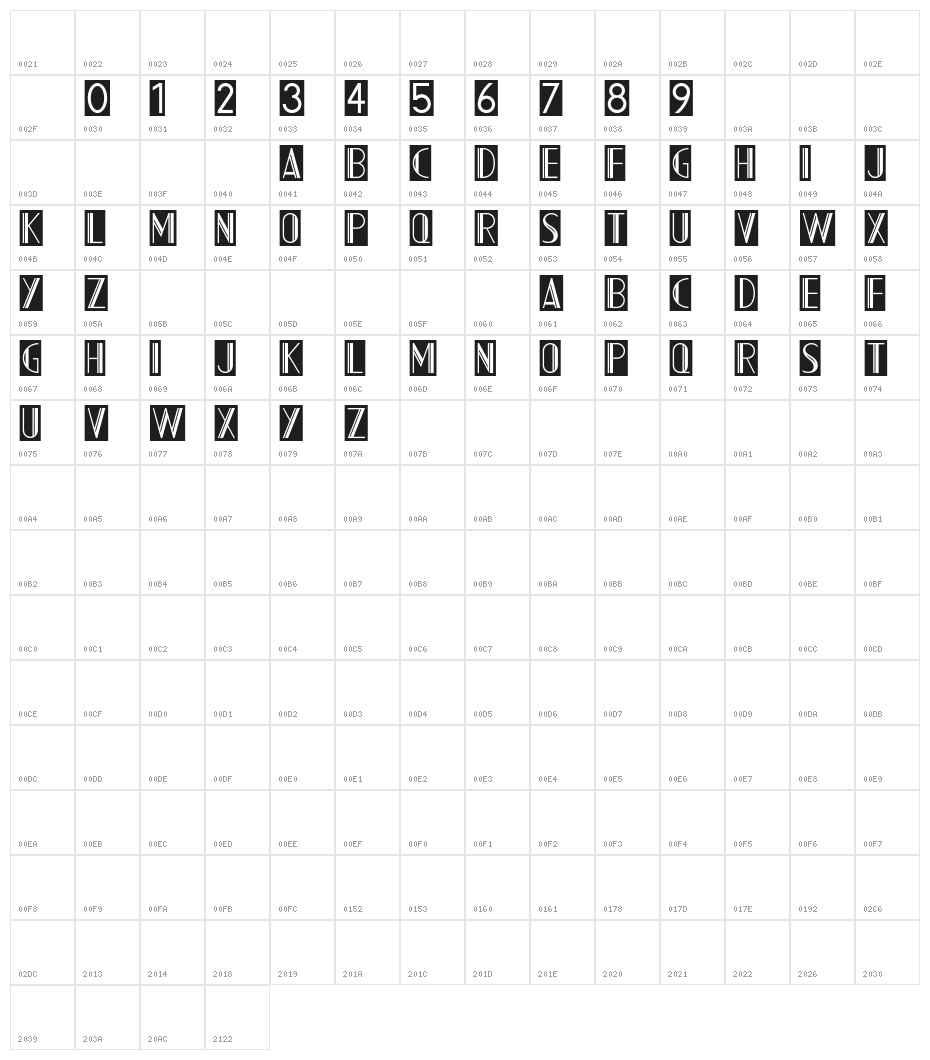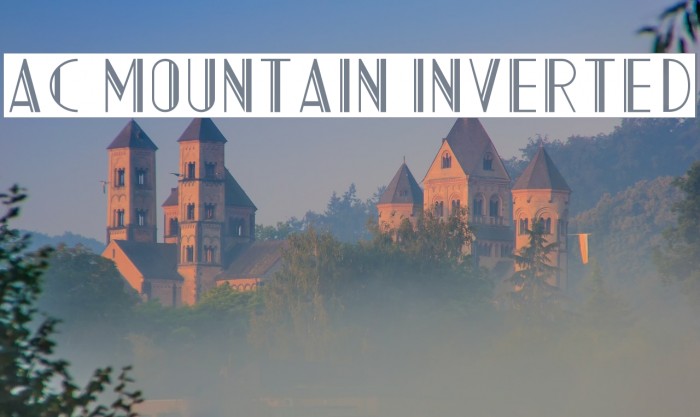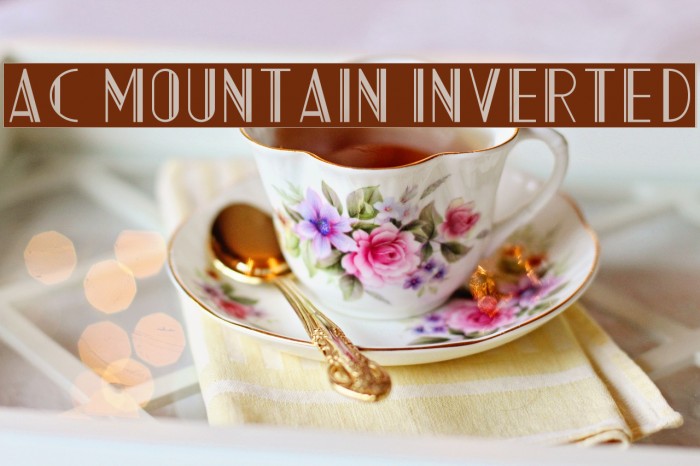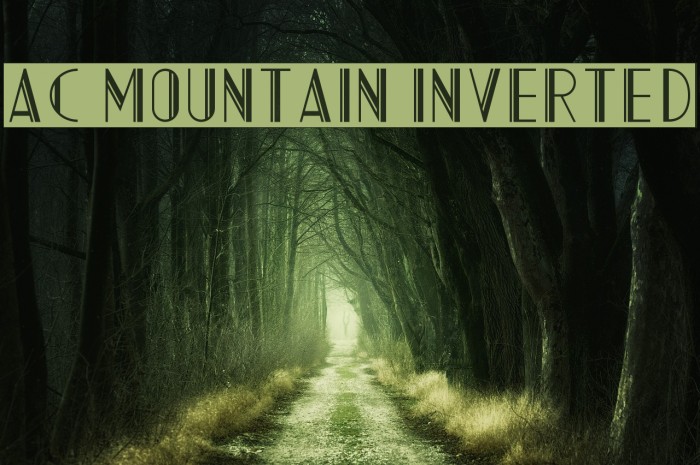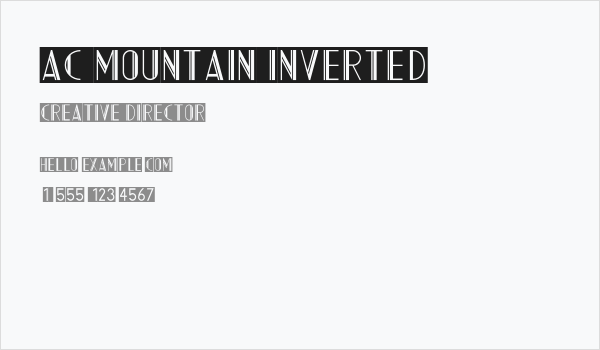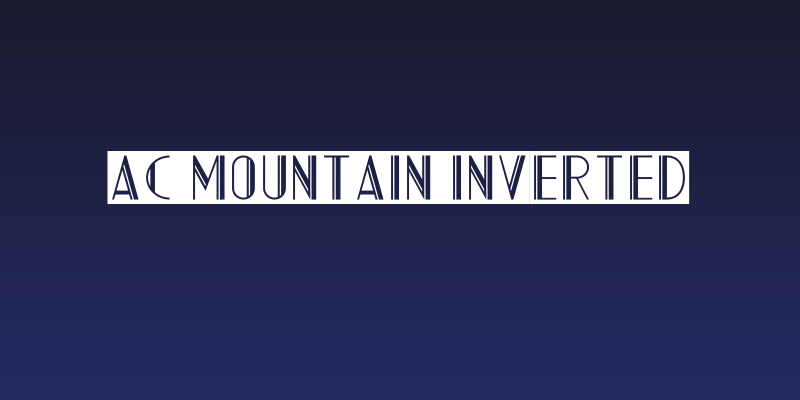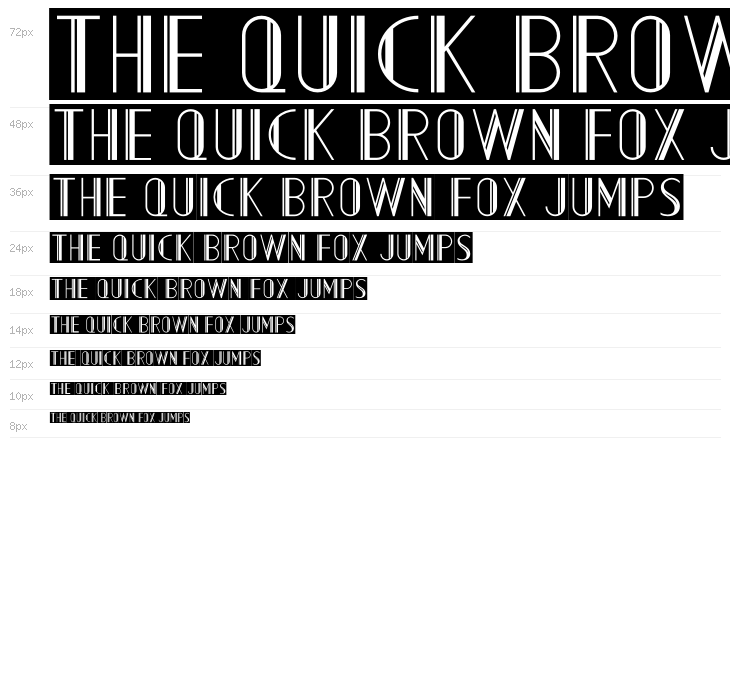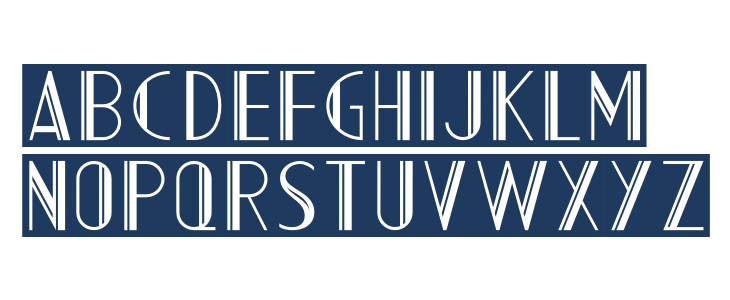
AC Mountain Inverted Font
✎ Art Deco
| Progetti proposti | Ideal for branding, posters, headlines, and any design project requiring a bold and modern aesthetic. |